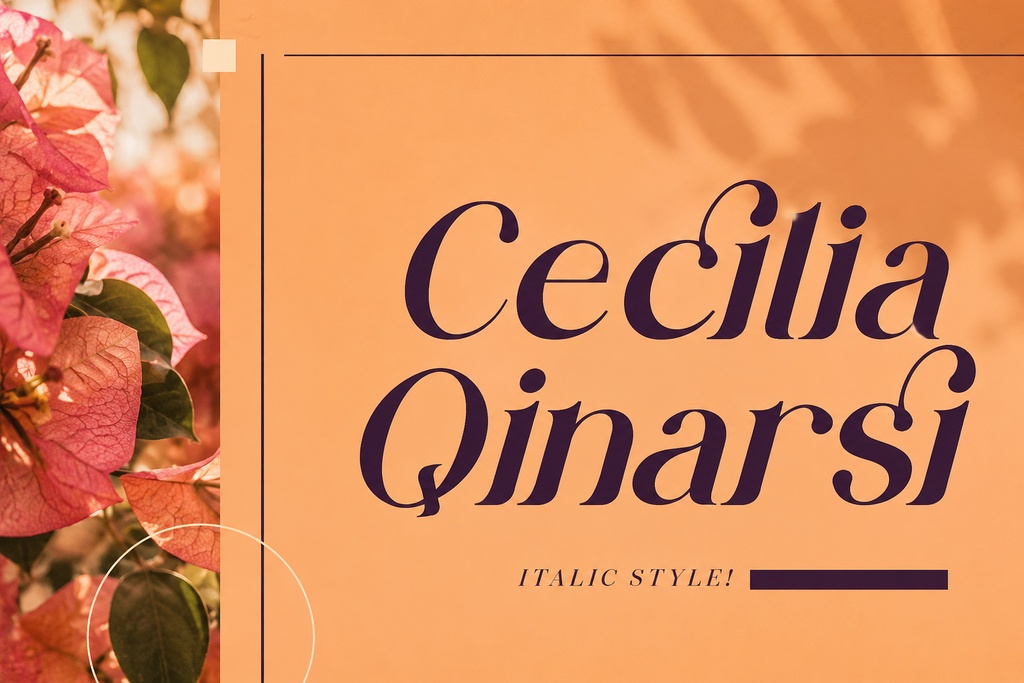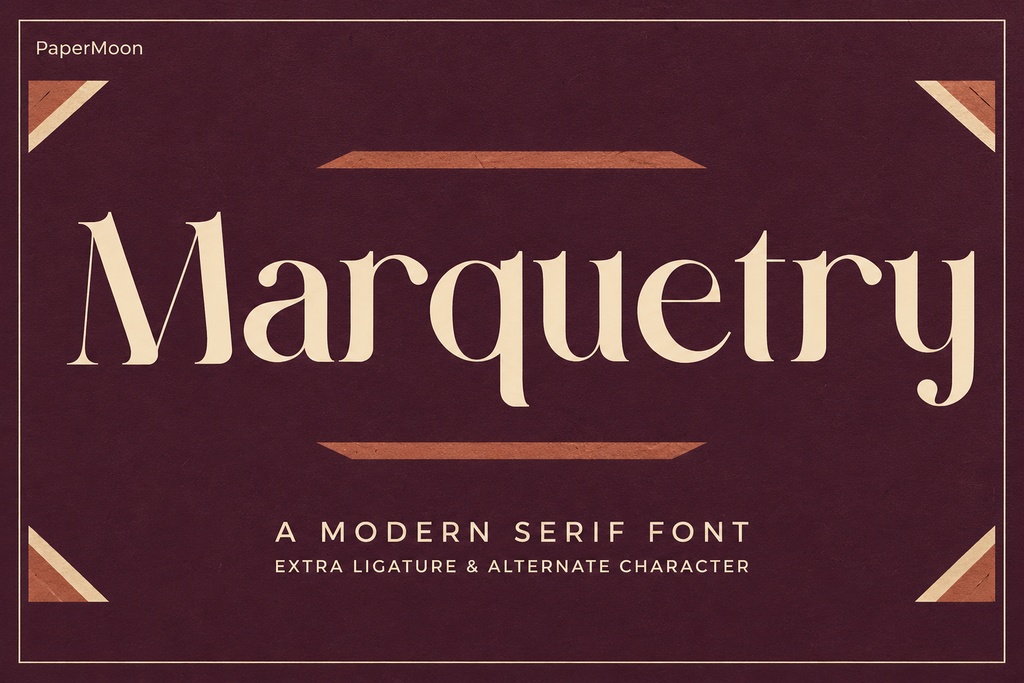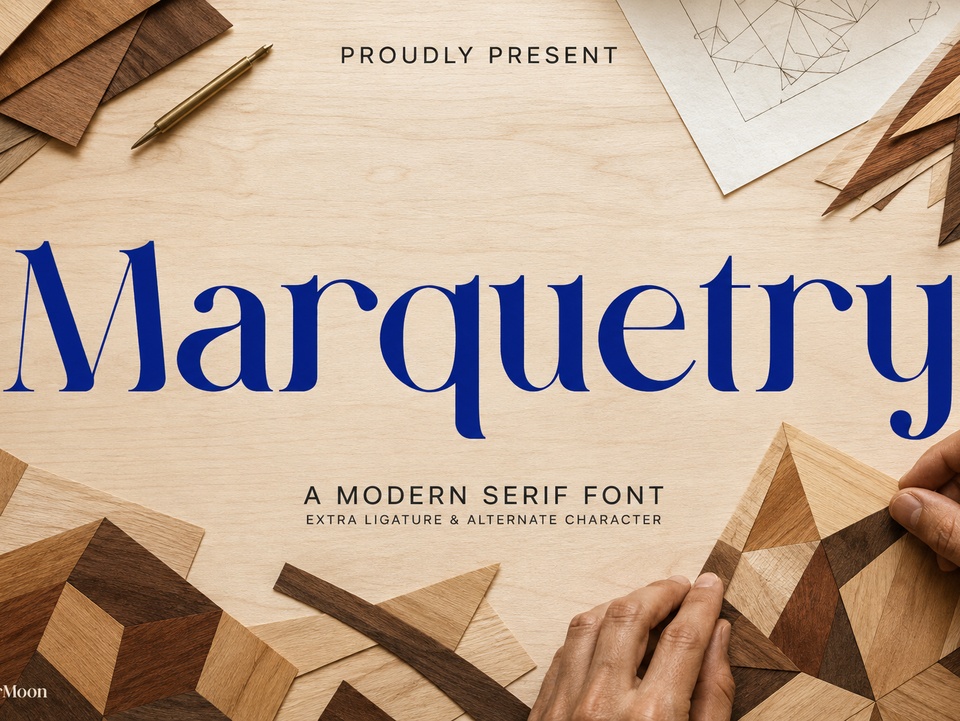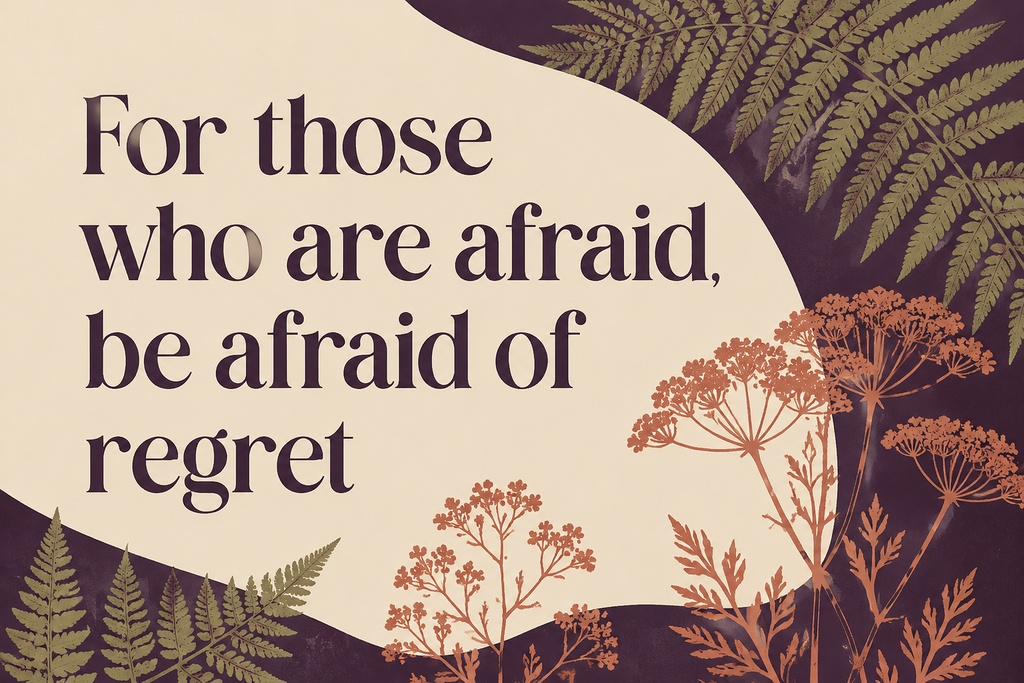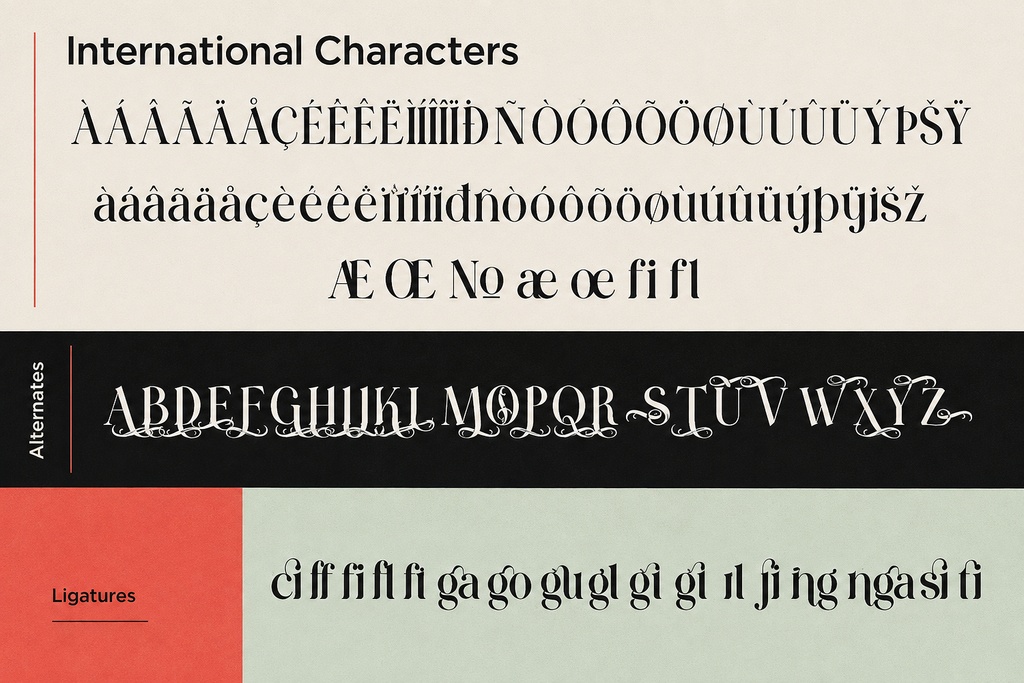
MARQUETRY モダンセリフフォント | ブランディング用ディスプレイ書体
**MARQUETRY**は、モダンで上質なセリフ書体と、表現力豊かなエディトリアル感、洗練されたラグジュアリーな雰囲気を兼ね備えたプレミアムフォントデュオです。RegularとItalicの2スタイルが組み合わさることで、ブランディング、パッケージ、招待状など、洗練されたセリフ体の存在感を際立たせたいさまざまなプロジェクトに、自信と個性のあるディスプレイタイポグラフィを提供します。 ### 内容 **MARQUETRY**にはRegularとItalicの2スタイルが収録されており、見出し、ワードマーク、キャプション、補足テキストなどに統一感のある正体と斜体の表現を使用できます。各スタイルには**276グリフ、279マッピング文字**が含まれています。Basic Latin、Latin-1文字およびアクセント付き文字に加え、7つのLatin Extended文字をサポートしています。**キリル文字とギリシャ文字には対応していません**ので、これらの文字体系が必要なプロジェクトで使用する場合は、事前に文字サポート範囲をご確認ください。 ### 主な特徴 フォントには、**liga**機能による標準合字、**salt**によるスタイル代替、**kern**によるカーニングが搭載されています。対応ソフトウェアでは、これらのOpenType機能を使用することで、より洗練された文字の組み合わせ、代替字形、そして最適化された文字間隔を実現できます。 2スタイルのフォントデュオは、デザインに明確な階層を作るのにも適しています。Regularは落ち着きのあるメインメッセージに、Italicは強調、名前、引用文、またはエディトリアルなアクセントとして使用できます。 ### 用途 このエレガントなセリフフォントは、以下のような幅広い用途におすすめです。 * ロゴ・ロゴタイプ * ラグジュアリーブランディング * エディトリアルレイアウト * 商品パッケージ * ホームウェア・生活雑貨 * ラベル * ショッピングバッグ * マグカップ * ポスター * 名言・引用デザイン * Tシャツ * ブックカバー * 名刺 * 招待状 * グリーティングカード * 特別なイベント用ステーショナリー * 写真用ウォーターマーク * SNS用グラフィック * ブティック商品キャンペーン * プレミアムマーケティング素材 **MARQUETRY**は、ファッションブランドのアイデンティティ、ホテルやレストランなどのホスピタリティブランド、美容ブランド、ブックカバー、洗練されたウェディング招待状などに、モダンなセリフ体の個性をプラスします。 ### パッケージ内容 商用Proパッケージには、以下の**MARQUETRY Regular**および**MARQUETRY Italic**が含まれています。 * OTF * TTF * WOFF * WOFF2 OTFおよびTTFファイルは、デスクトップデザインや対応するクリエイティブアプリケーションで使用できます。WOFFおよびWOFF2ファイルは、適切なCSS **@font-face**設定を使用するWebプロジェクト向けに提供されています。 ### 対応ソフトウェア OTFまたはTTFフォントに対応するさまざまなソフトウェアで使用できます。対応例: * Adobe Photoshop * Adobe Illustrator * Adobe InDesign * Microsoft Word * Canva * Procreate * Figma * Affinityシリーズ * Cricut Design Space * Silhouette Studio * その他の対応デザインソフトウェア OpenType機能の利用可否や操作方法は、アプリケーションによって異なる場合があります。 ### ライセンス クライアントワーク、商用ブランディング、マーケティング、デジタルデザイン、物理製品、販売用商品などに使用する場合は、付属のPaperMoonライセンス規約に従い、**Cubebrush Commercial License**を選択してください。 フォントファイルを単独のアセットとして再配布することは禁止されています。個人利用および非商用目的の場合は、**Basic License**をご利用ください。 このフォントデュオの推奨価格は**15 USD**です。2スタイルのフォントファミリーとして、現在のCubebrushにおける**9~18 USD程度の価格帯**に位置する商品です。 ### MARQUETRYで洗練されたデザインを 洗練されたエディトリアルセリフ、モダンなラグジュアリー感、そして柔軟なRegular&Italicの組み合わせを、次のブランディング、パッケージ、招待状プロジェクトに取り入れてみてください。 **MARQUETRY**は、上品さと現代的な個性を求めるデザインに、洗練されたタイポグラフィの魅力を加えます。